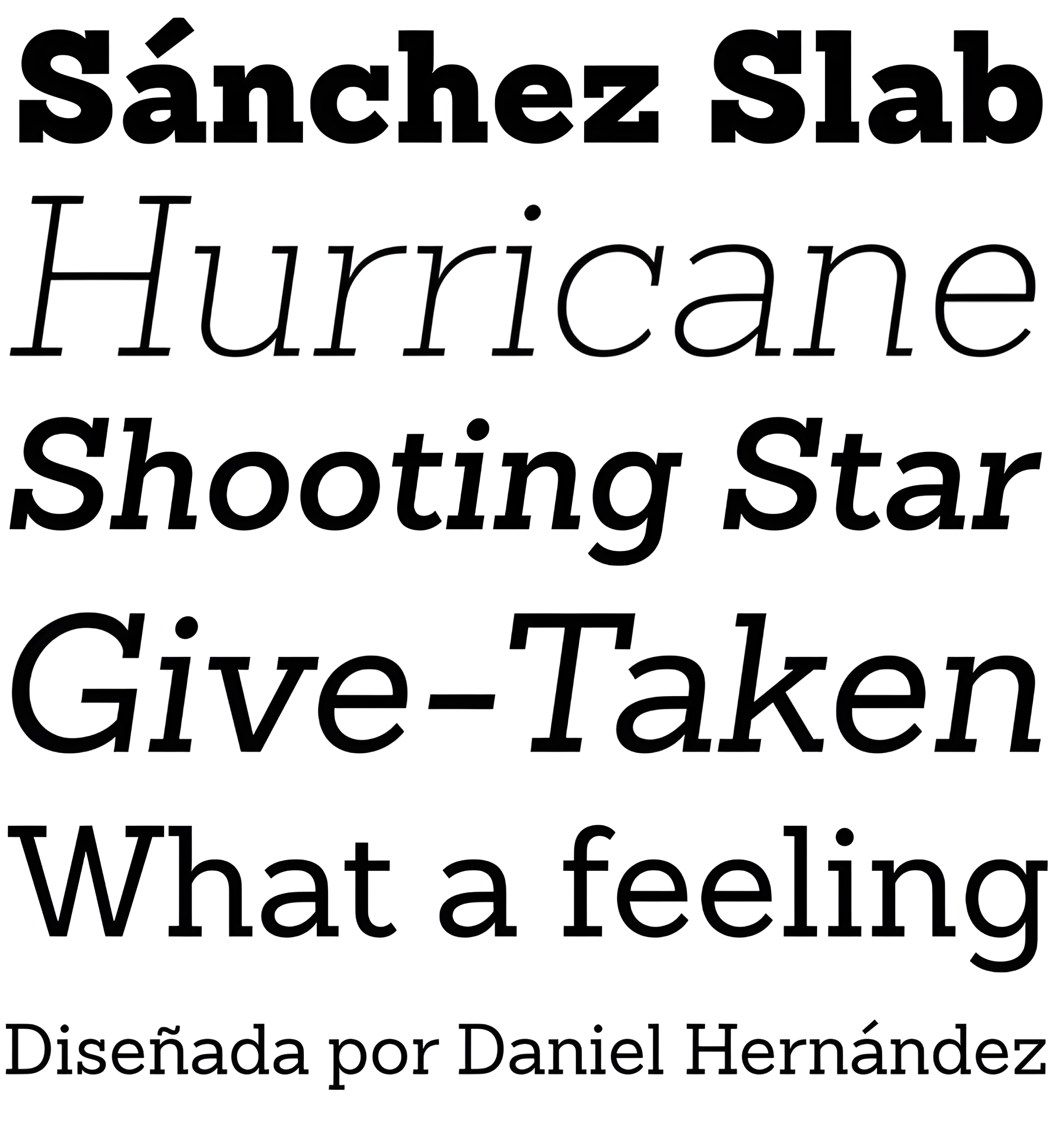
| Año | 2013 |
| Créditos | Daniel Hernández |
| Descripción | Sánchez, diseñada por Daniel Hernández, es un tipo de letra con gracias perteneciente a la clasificación slab serif, o egipcia, que guarda un gran parecido con la icónica Rockwell. Ofreciendo contraste y equilibrio a la estructura cuadrada, Sánchez Slab es una nueva versión, más robusta y con bordes rectos, que le confieren mayor carácter y potencia. Sánchez Slab consta de 12 variantes, que van desde la extra clara a la negra, cada una con la misma altura x. Las variantes Regular e Italic están disponibles gratuitamente. |
| Familia(s) | ExtraLight, ExtraLight Italic, Light, Light Italic, Regular, Italic, SemiBold, SemiBold Italic, Bold, Bold Italic, Black, Black Italic |
| Estilos | 12 |